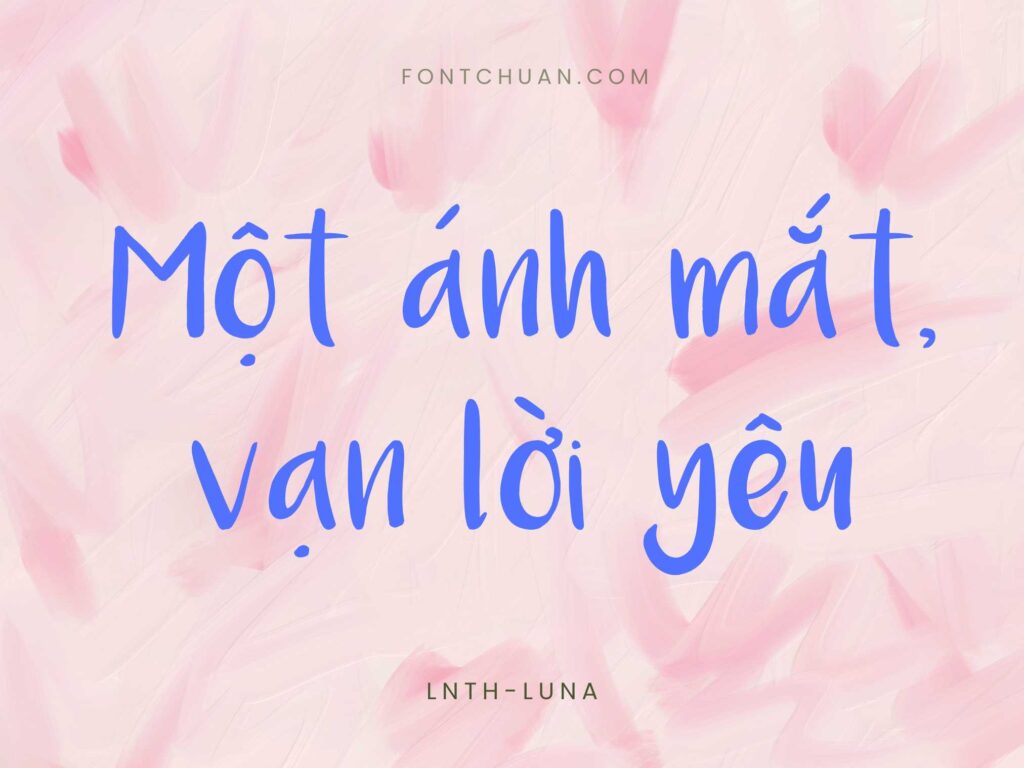
Font LNTH Luna Việt Hóa
Font Luna là một kiểu chữ viết tay mềm mại, mang phong cách hiện đại và nữ tính. Với các đường nét thanh thoát, nhẹ nhàng, font này mang lại cảm giác tinh tế, sang trọng và rất phù hợp cho các thiết kế về thời trang, làm đẹp, thiệp mời hoặc branding thương hiệu cao cấp. Luna giúp tạo ra những thiết kế đầy nghệ thuật, mang đậm dấu ấn cá nhân
Phiên bản này đã được Việt hóa bởi LNTH, hỗ trợ đầy đủ tiếng Việt cùng hơn 50 ngôn ngữ khác, giúp người dùng dễ dàng ứng dụng trong thiết kế quốc tế. Font Luna được các thành viên Font Chuẩn sưu tầm và đăng tải nhằm mang đến một sự lựa chọn tinh tế và sang trọng, đặc biệt phù hợp với các dự án cần sự mềm mại, nhẹ nhàng
Về đặc điểm thiết kế, Luna có cấu trúc chữ thanh mảnh, hơi nghiêng nhẹ, tạo cảm giác tự nhiên và trang nhã. Kiểu chữ này rất phù hợp để sử dụng trong thiết kế bao bì sản phẩm, logo, thiệp mời hoặc các ấn phẩm sáng tạo có yếu tố thư pháp hiện đại
Font Luna được ứng dụng rộng rãi trong các sự kiện như thiệp cưới, Valentine hoặc các thiết kế mang phong cách trang nhã. Nó phù hợp với nhiều ngành nghề như quảng cáo, spa, ẩm thực, giáo dục